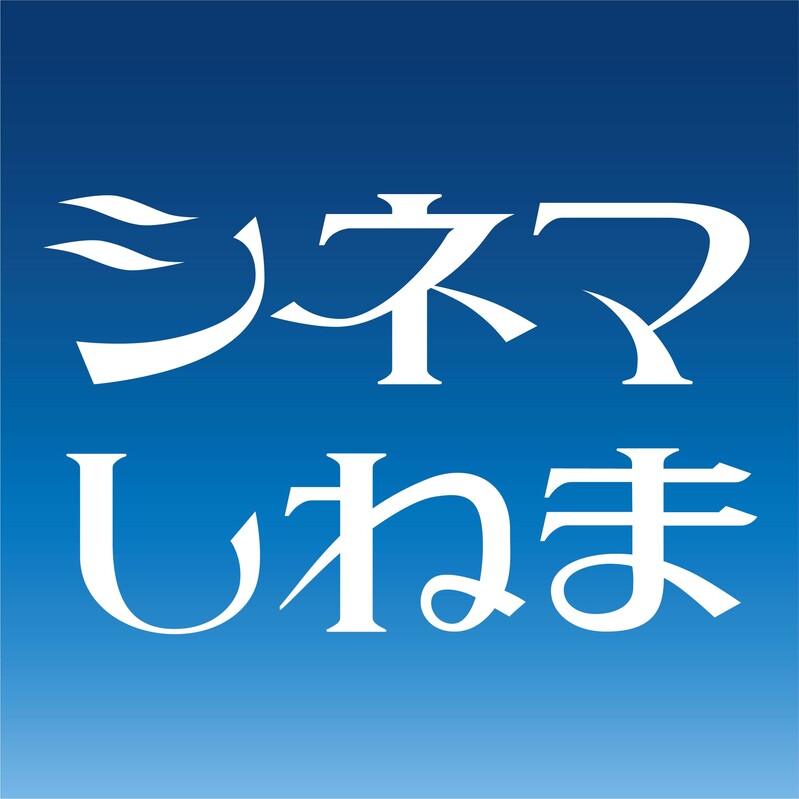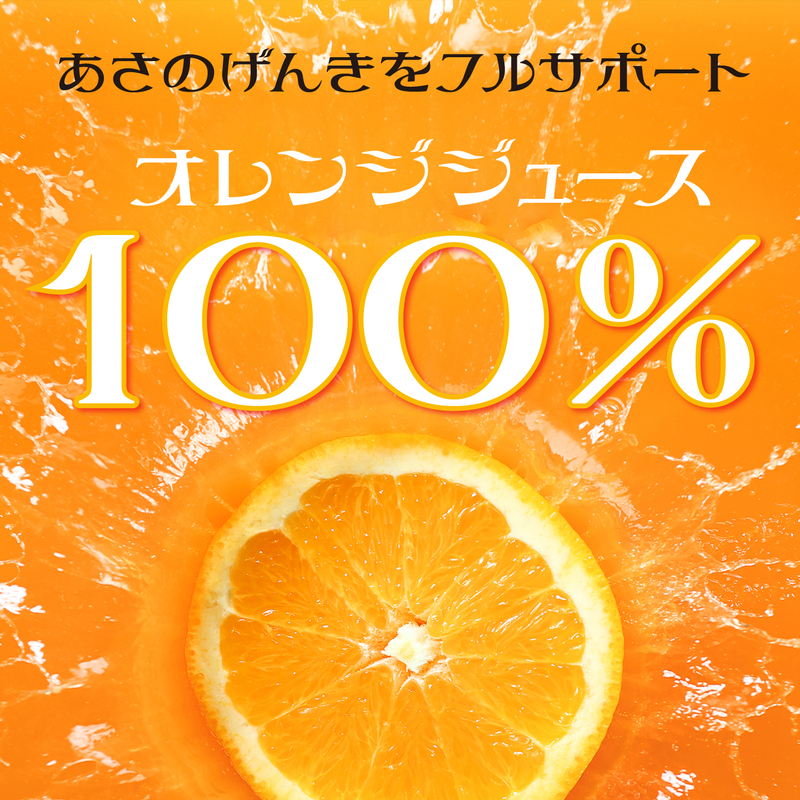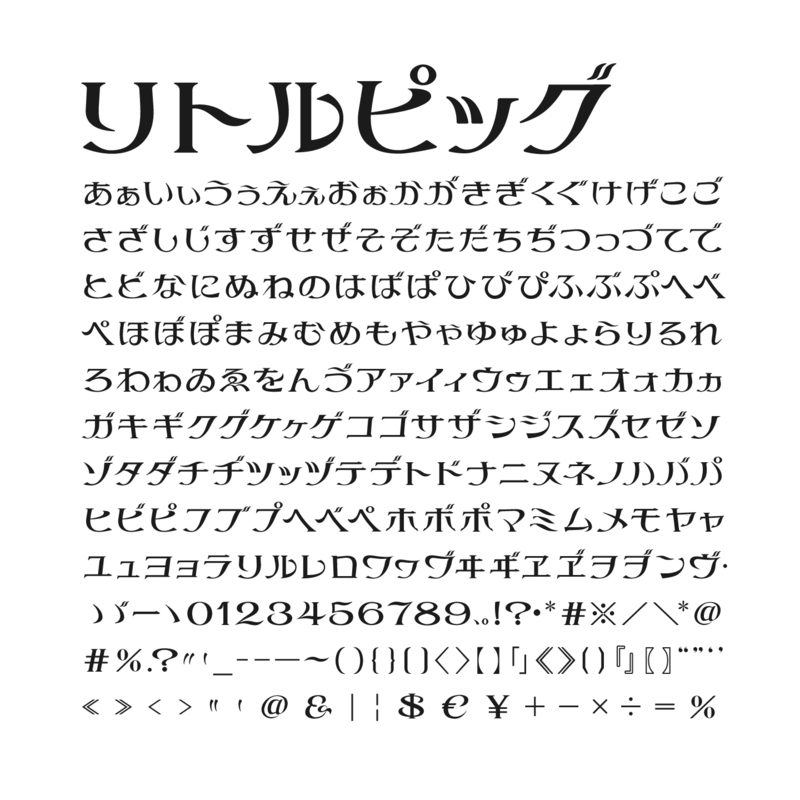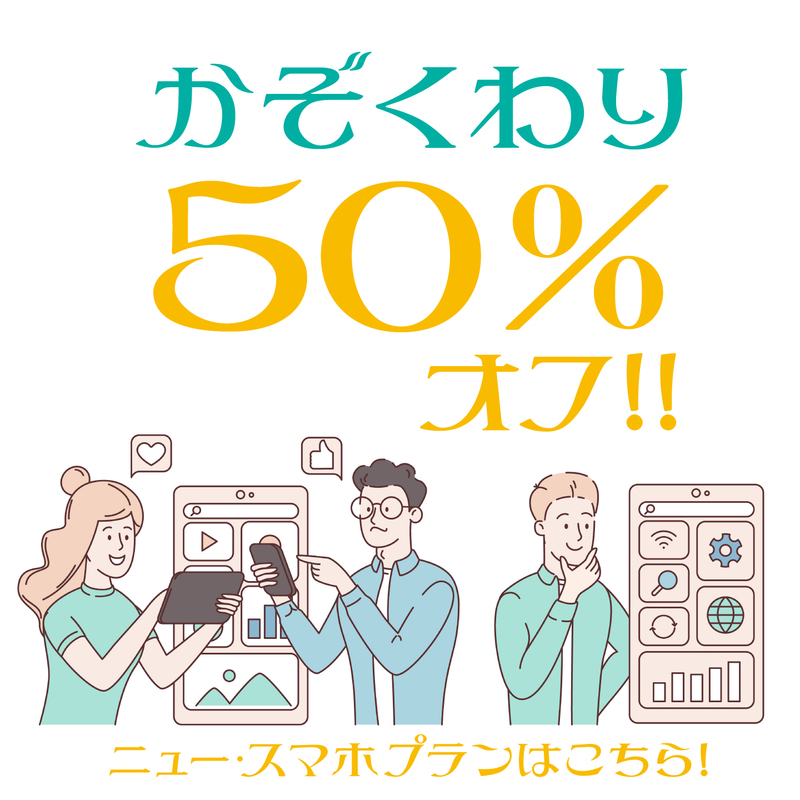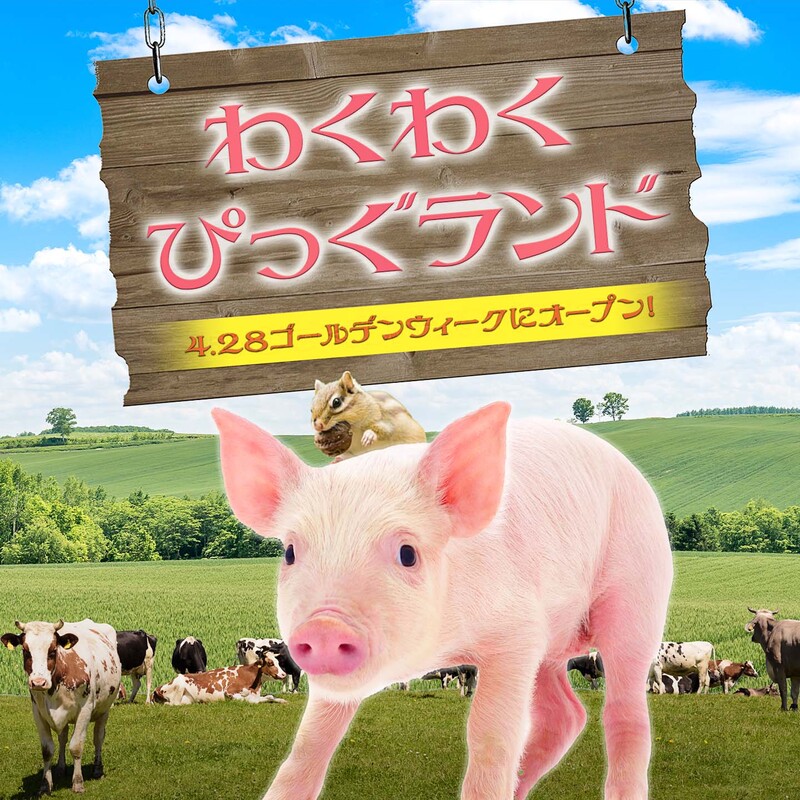
リトルピッグ|Chiba Design|和文・欧文・デザイン書体のダウンロード販売|フォントファクトリー
ゆるいカーブが独特なフォント。可愛いコブタのイメージでフォント化しました。ショップのロゴ、メニューリストの作成などに便利です。カタカナ&ひらがな、数字、約物のみ・アウトライン抽出可。商用利用OKです。